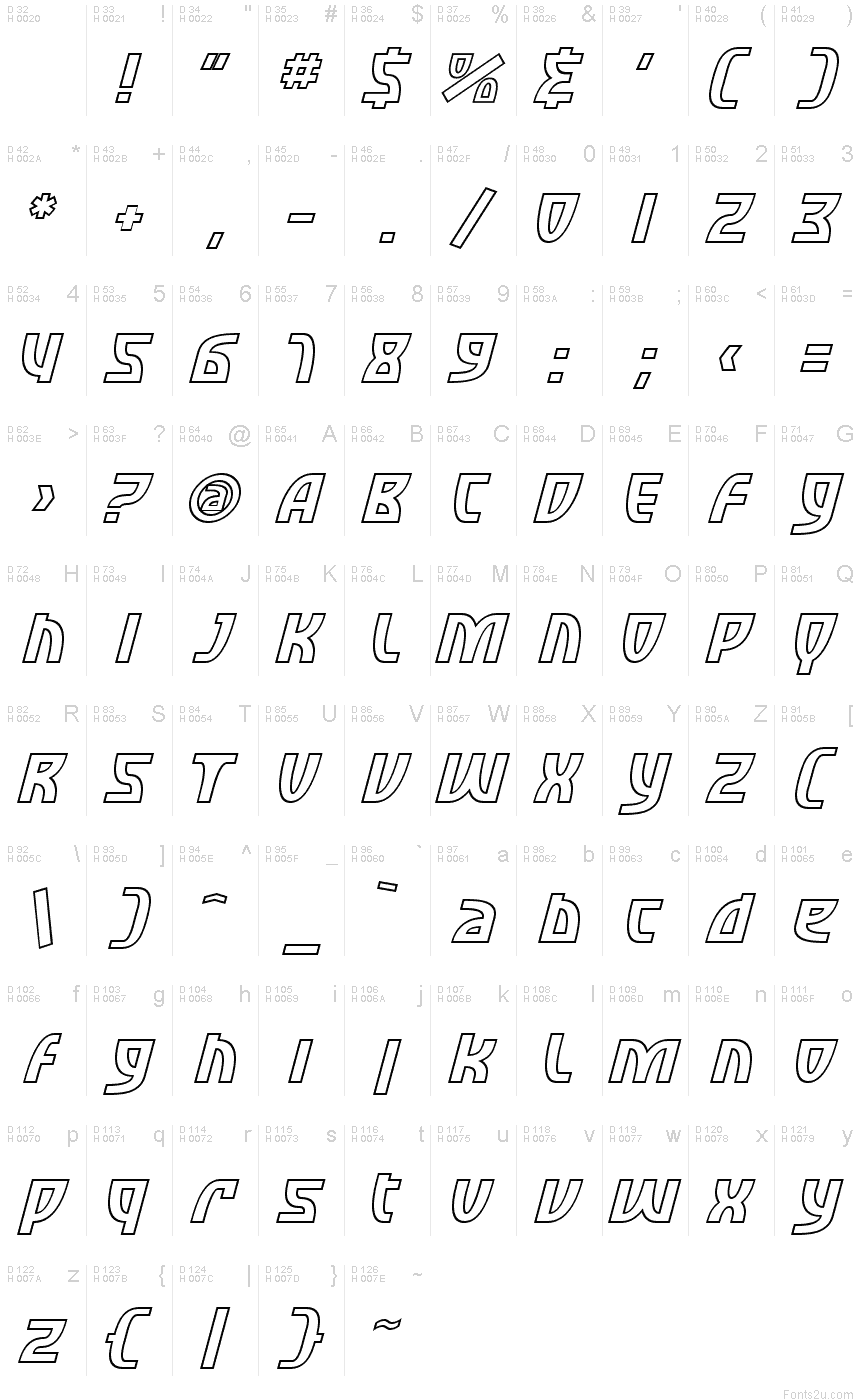
SF Retroesque Outline Italic
SF Retroesque Outline Italic von ShyFonts Type Foundry ist eine kostenlose Retro-Outline-Display-Schrift mit einem dynamischen Schwung des späten 20. Jahrhunderts. Die Buchstaben wirken breit und aerodynamisch; abgerundete Ecken und sanfte Bögen verleihen dem Alphabet einen weichen Rhythmus des Maschinenzeitalters statt eines harten Sci-Fi-Looks.
Sie eignet sich perfekt für Poster-Schlagzeilen, Arcade-Branding, Schallplattencover, Titelkarten und Event-Flyer, bei denen eine kostenlose Schrift Bewegung vermitteln soll, ohne dabei überladen zu wirken. Da die Kontur offen bleibt und die kursive Neigung so präsent ist, funktioniert sie auch hervorragend für kurze Cover-Zeilen, Monogramme und große Initialen, die einen luftigen Retro-Touch benötigen.